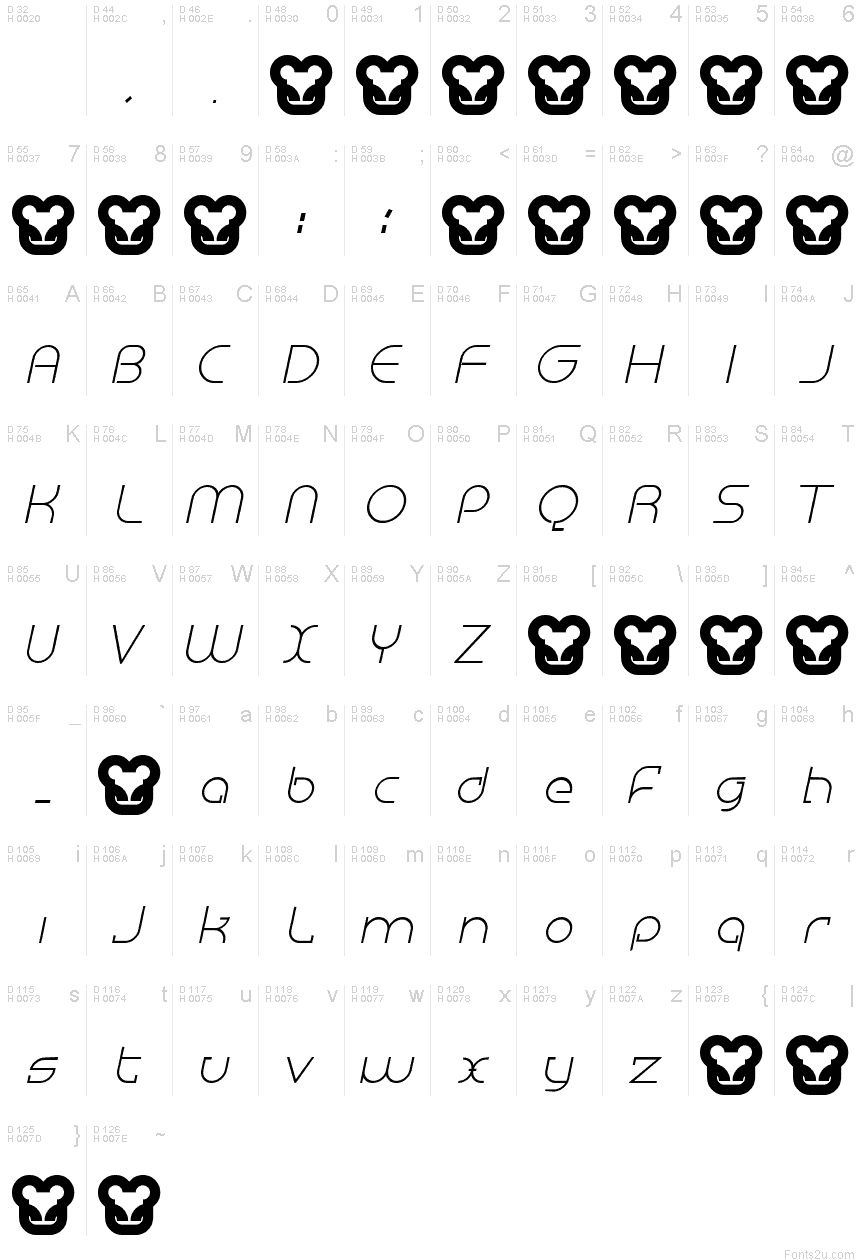
Megalomania Italic to darmowy, kursywny krój typu display o zaokrąglonych, jednolitych literach i łagodnym pochyleniu, które nadaje kształtom płynny, futurystyczny charakter. Litery pozostają otwarte i proste, a miękkie krzywizny oraz długie, ukośne cięcia sprawiają, że projekt jest wyrazisty, ale nieprzeładowany.
Megalomania Italic świetnie sprawdza się w tytułach plakatów, logotypach, okładkach albumów, ulotkach i krótkich tekstach na opakowaniach, gdzie potrzebny jest opływowy krój typu display, który „niesie” kompozycję. Ten darmowy font doskonale pasuje też do brandingu, grafik w social mediach i nagłówków – jego dynamiczny rytm i zaokrąglone narożniki tworzą czystą, charakterystyczną linię nawet przy niewielkiej ilości tekstu.